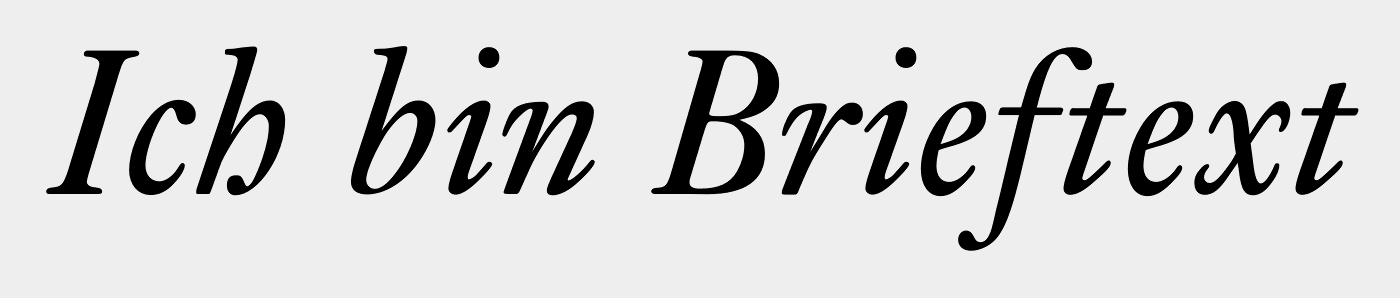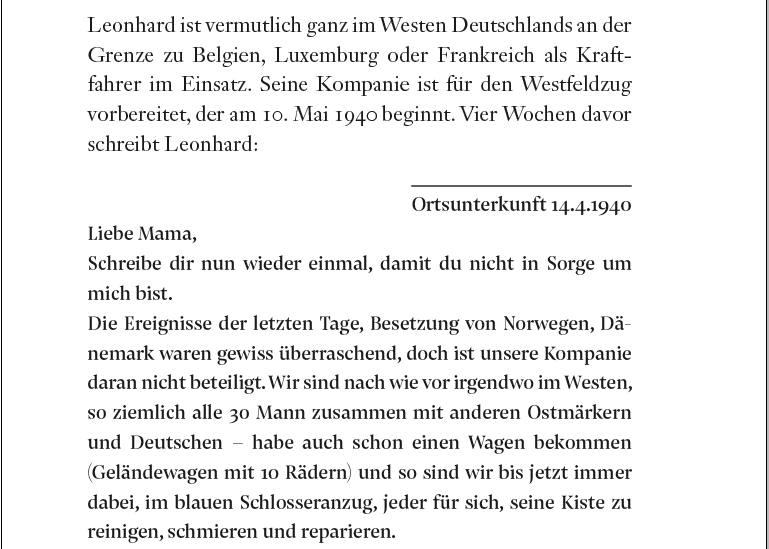
1940er Jahre Brief-Fließtext für Buch
ich suche eine Fließtextschrift für ein Buchprojekt mit (teils längeren) Briefen aus den 1940er Jahren – eingeschoben in normalen Fließtext, den ich zunächst in der Janson gesetzt habe.
Fällt euch da was ein? Ich habe die Briefe erst mal in der Futura gesetzt, weil sie zum Teil handschriftlich, zum Teil mit der Maschine geschrieben sind, und ich  daher einen handschrift- oder maschinenschriftartigen Font vermeiden wollte. Die Futura geht eh, ist aber natürlich sachlicher, als ich die Briefe gerne sehen würde. Könnte eine andere Serifenschrift zur Janson passen?
Nachdem der Italic-Schnitt sich ja  deutlich vom aufrechten abhebt, würde ich diesen für die Briefe ausprobieren.
Für gewöhnlich empfiehlt es sich nicht, Serifenschriften zu mischen, da es dem ungeschulten Auge wenig bis nicht auffällt.
Wäre es möglich, die Briefe einfach in Kursiv zu setzen beziehungsweise durch Einrückung deutlich zu machen, dass es kein Fließtext ist?
Das habe ich in einer anderen Version versucht. Geht, ja, aber das war mir etwas zu naheliegend, bzw. ist dann schon sehr viel kursiver Text zu lesen. Wenn es eine gerade Lösung gäbe, wäre es mir lieber. Aber die Kursivvariante ist Plan B.
Würde ich wie @Phoibos auch erstmal vermeiden. Dazu kombinieren lässt sich dennoch so viel, dass ich mir ein paar mehr Anhaltspunkte wünschen würde, um die riesige Auswahl konstruktiv einzugrenzen.
Zum Beispiel:
• Welches Thema?
• Welche Zielgruppe?
• Welche Sprachunterstützungen?
• Gewünschte Ziffernvielfalt?
• Braucht man Kapitälchen?
• Braucht man ein ẞ?
Ich würde auch eher zu einer humanistischen Sans als zur Futura raten.
•
2. Weltkrieg
Biographie
Deutsch
Normale Ziffernvielfalt
Kapitälchen gerne, aber kein Muss
ß wird verwendet
Janson und Pensum Display?
Mir wäre der Kontrast zu stark, da die Pensum viel dunkler erscheint. Zudem hast Du es mit Fließtext zu tun und da sind Displayschriften eher ungeeignet.
Hier haben wir ein paar Schriftpaarungen zusammengestellt:
Ist die Janson eine conditio sine qua non? Denn Paarungen kann man nach vielen Aspekten zusammenstellen, hier würde gleicher Autor oder gleiche Zeit (soweit mir bekannt) schon mal wegfallen.
Nein, hatte sie nur als zumindest einen Fixpunkt mal festgelegt. Morgen muss es schon zur Abgabe und die Janson war schon „gekauft“.
möchte trotzdem nochmal das thema schreibmaschinenschrift einwerfen. da wäre der bezug zum brief sehr klar und direkt. die kleine unschärfe, dass ja nicht alle briefe mit der maschine sondern manche auch mit der hand geschrieben waren, würde mich jetzt nicht stören. nicht gerade die american typewriter, aber eine courier oder durchaus auch PT mono fände ich passend (muss ja nicht notwendigerweise eine aus den 40ern sein).
Danke, die werde ich mir mal anschauen. Bisher hab ich einige probiert, aber für längere Textpassagen hat mir noch keine gepasst.
Für eine Schreibmaschinenschrift bitte auch auf der Seite von Catfont nachsehen.
Genau! Die Erika mit Glyphrotation wäre momentan mein Favorit für das Thema, wenn es eine Schreibmaschinenschrift werden soll. :nicken: